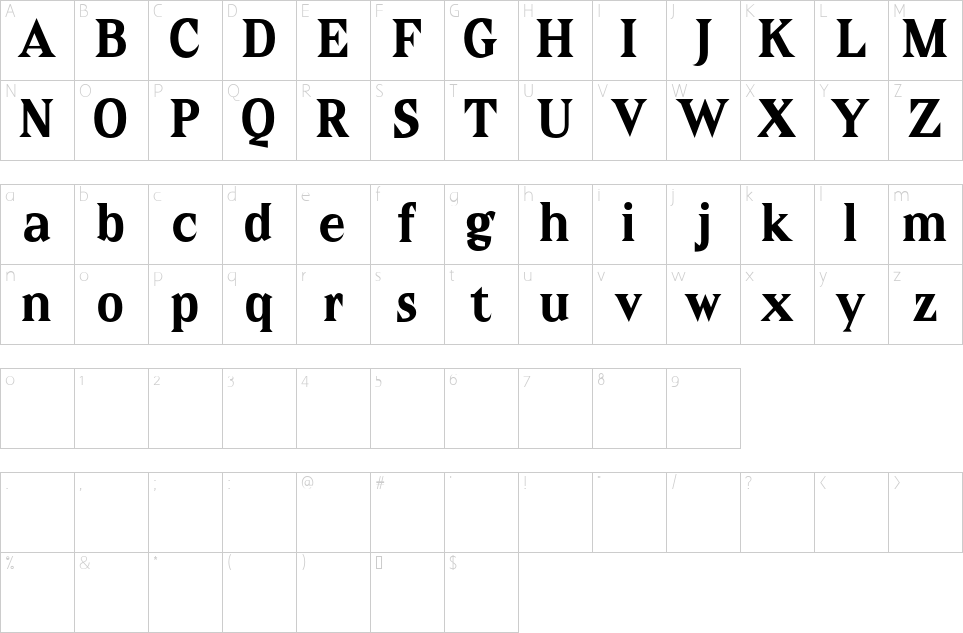
Gerfard Font
A fonte Gerfard é uma opção gratuita para designers e criativos que buscam uma solução amigável para seus projetos digitais no Windows e Mac. Desenvolvida pela Craft Supply Co, esta fonte vem de um designer talentoso que proporciona uma variedade de opções para estilos variados. Com 177 downloads registrados até o momento, Gerfard oferece uma ótima solução para quem busca alternativas gráficas leves e legíveis em qualquer plataforma. Ideal para criações digitais do dia a dia, como design de sites ou projetos básicos de design gráfico, esta fonte é perfeita para quem valoriza a qualidade sem comprometer com os custos. Não hesite em explorar e descobrir por si mesmo as possibilidades criativas desta fonte gratuita e elegante.
Mapa de caracteres da fonte Gerfard Font